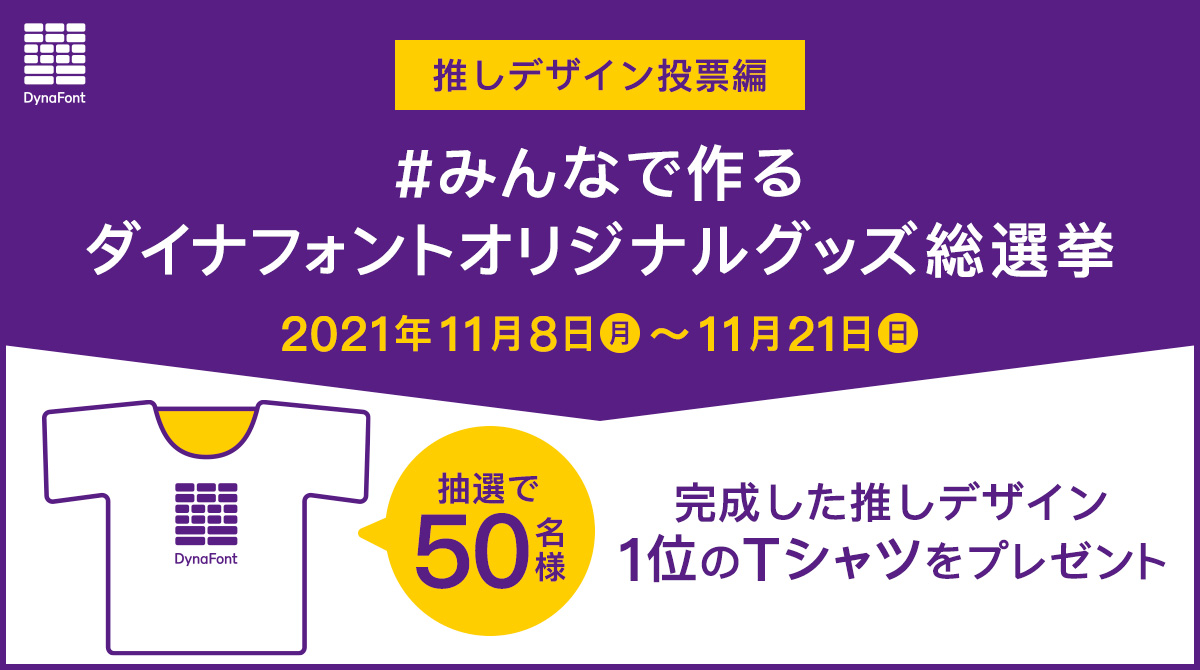
- みんなで作るダイナフォントオリジナルグッズ総選挙 【推しデザイン投票編】推しグッズはTシャツに決定! 3種類のデザインから投票しよう!抽選で50名に完成した推しデザイン1位のTシャツをプレゼント
ダイナコムウェアは、2021年11月8日(月)から11月21日(日)の期間中、「【推しデザイン投票編】#みんなで作るダイナフォントオリジナルグッズ総選挙」を開催。
「みんなで作るダイナフォントオリジナルグッズ総選挙」は、制作して欲しいグッズに投票してもらう【推しグッズ投票編】と、投票第1位に選ばれたグッズにダイナフォントを使用したデザインから投票してもらう【推しデザイン投票編】の2回にわたる選挙となる。
今回の「【推しデザイン投票編】 #みんなで作るダイナフォントオリジナルグッズ総選挙」の投票者から抽選で50名に、推しデザイン第1位に選ばれたTシャツをプレゼントされる。
【推しグッズ投票編】推しグッズ結果発表!投票結果ベスト3
2021年9月15日(水)から9月30日(木)の期間中「【推しグッズ投票編】#みんなで作るダイナフォントオリジナルグッズ総選挙」を開催した。
「【推しグッズ投票編】#みんなで作るダイナフォントオリジナルグッズ総選挙」は、これまで数々のダイナフォントオリジナルグッズを制作してきたダイナコムウェアが選抜した、ホテル型キーホルダー、Tシャツ、ファイバークロス、トートバッグ、フレークシール、紙製コースター、缶バッジの7品目から、制作して欲しいグッズを投票する選挙。
投票の結果、第3位「ファイバークロス」、第2位「トートバッグ」、そして第1位に選ばれた「Tシャツ」が推しデザイン投票編へ進出することになった。
【推しデザイン投票編】 #みんなで作るダイナフォントオリジナルグッズ総選挙 選抜3デザイン
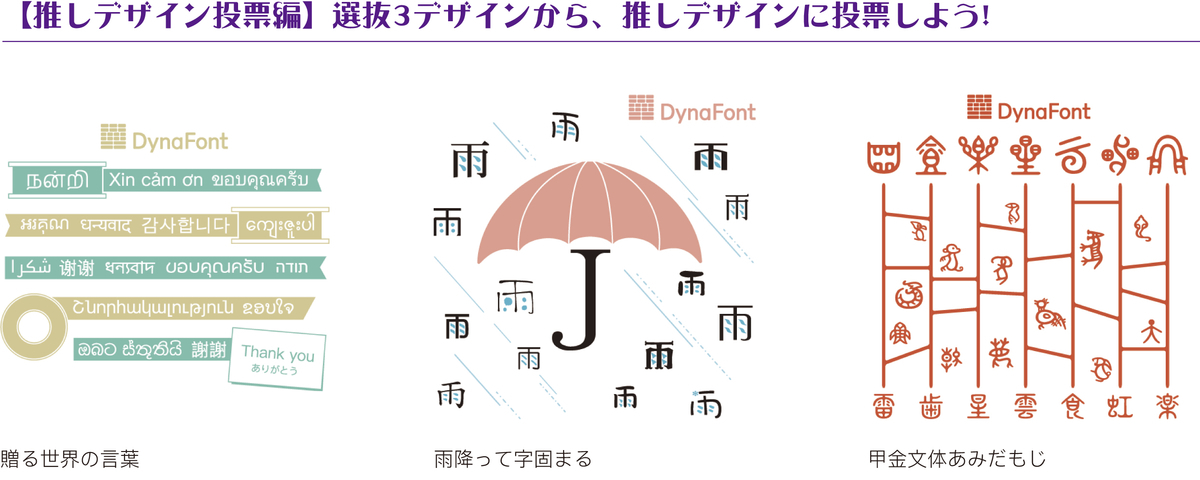
選抜3デザインその1:贈る世界の言葉
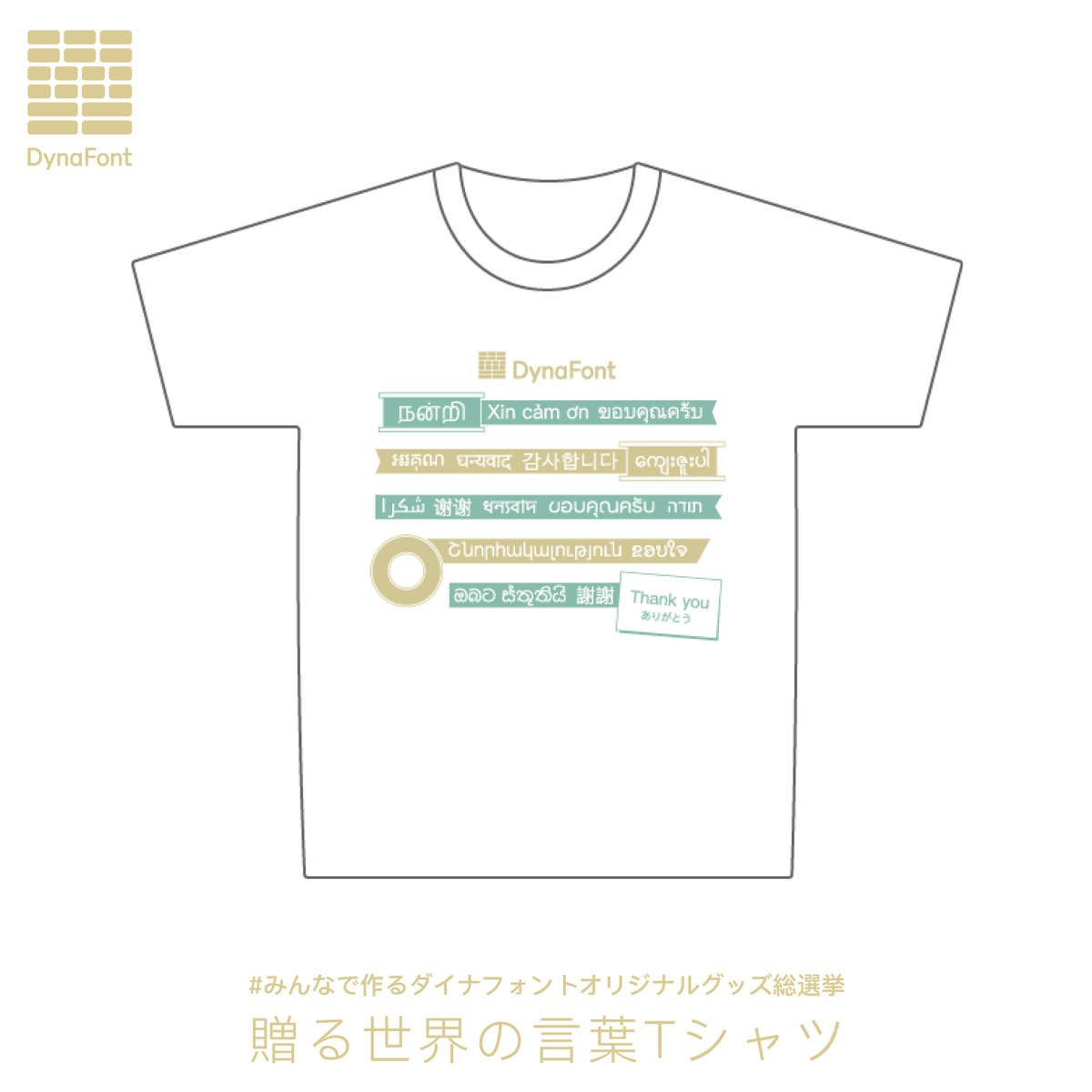
ラッピングリボンと世界各国の言語で表現した「ありがとう」で感謝の贈りものとして、国境を越えて世界中に伝わるデザインを心掛けました。「ありがとう」の文字は18種類の言語を同一スタイルのデザインで使用できる「金剛黒体 多言語」を使用している。
選抜3デザインその2:雨降って字固まる
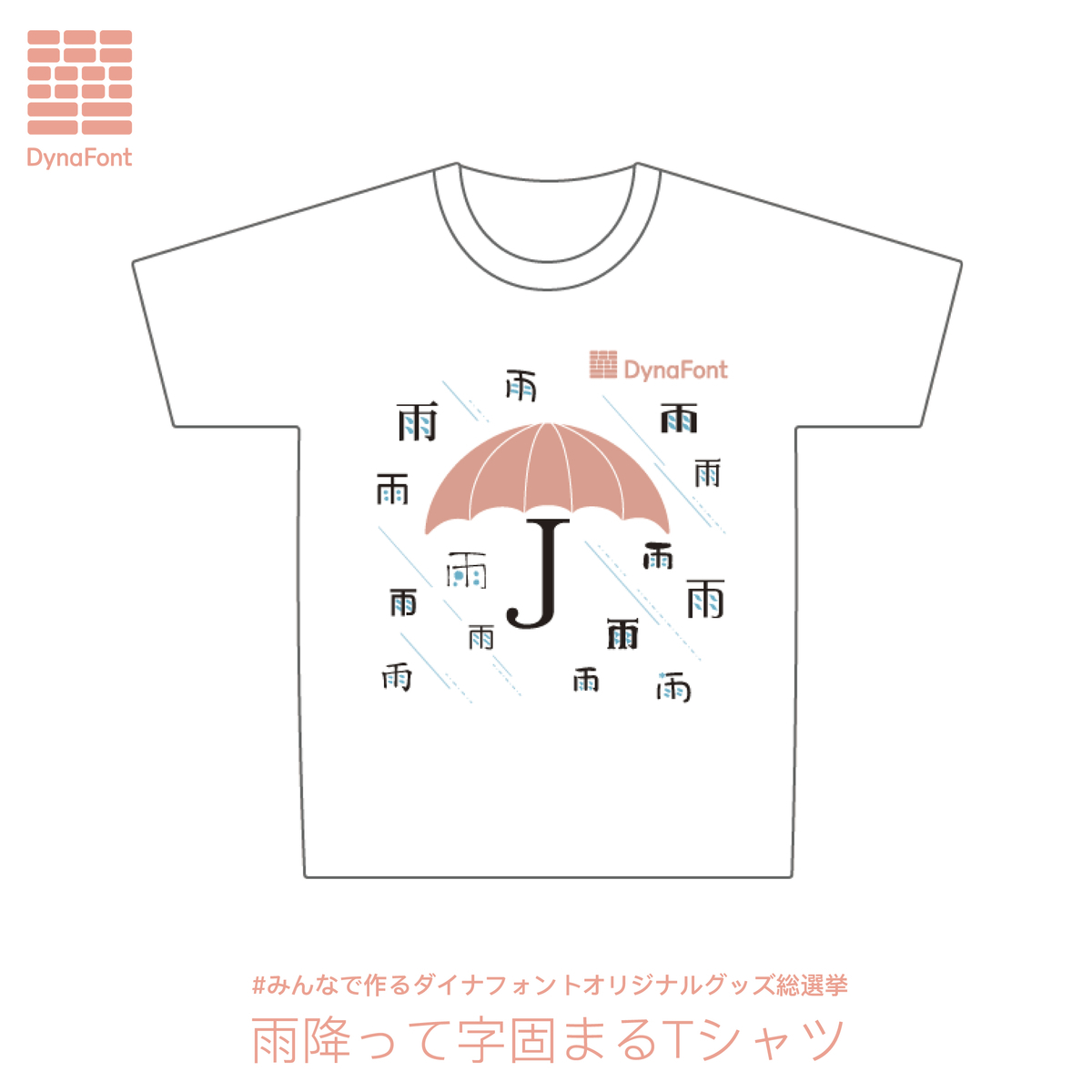
雨降って地固まるということわざもあるが、雨の文字を表現したように豊富な書体のダイナフォントなら、書体選びに悩んだときも希望通りの書体がきっと見つかって気分も晴れ晴れなデザインとなる。
傘の柄のJの部分の文字は優雅宋。
選抜3デザインその3:雨降って字固まるTシャツ
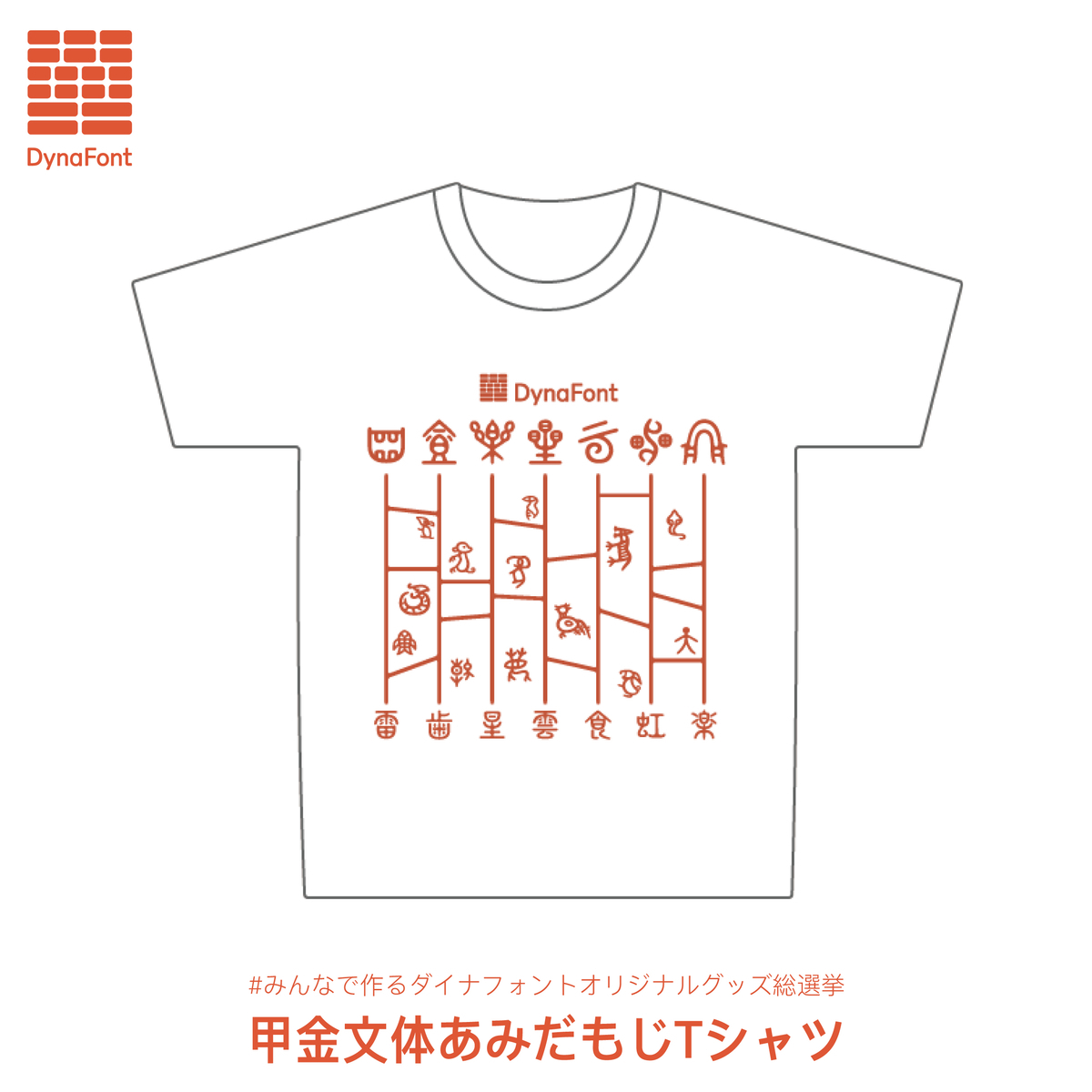
異体字として象形文字も使える古代文字の美しさを追求した書体「甲金文体」。それぞれの象形文字のあみだくじを辿ることで該当する漢字が判明する、遊び心にあふれた「あみだもじ」なデザインとなる。